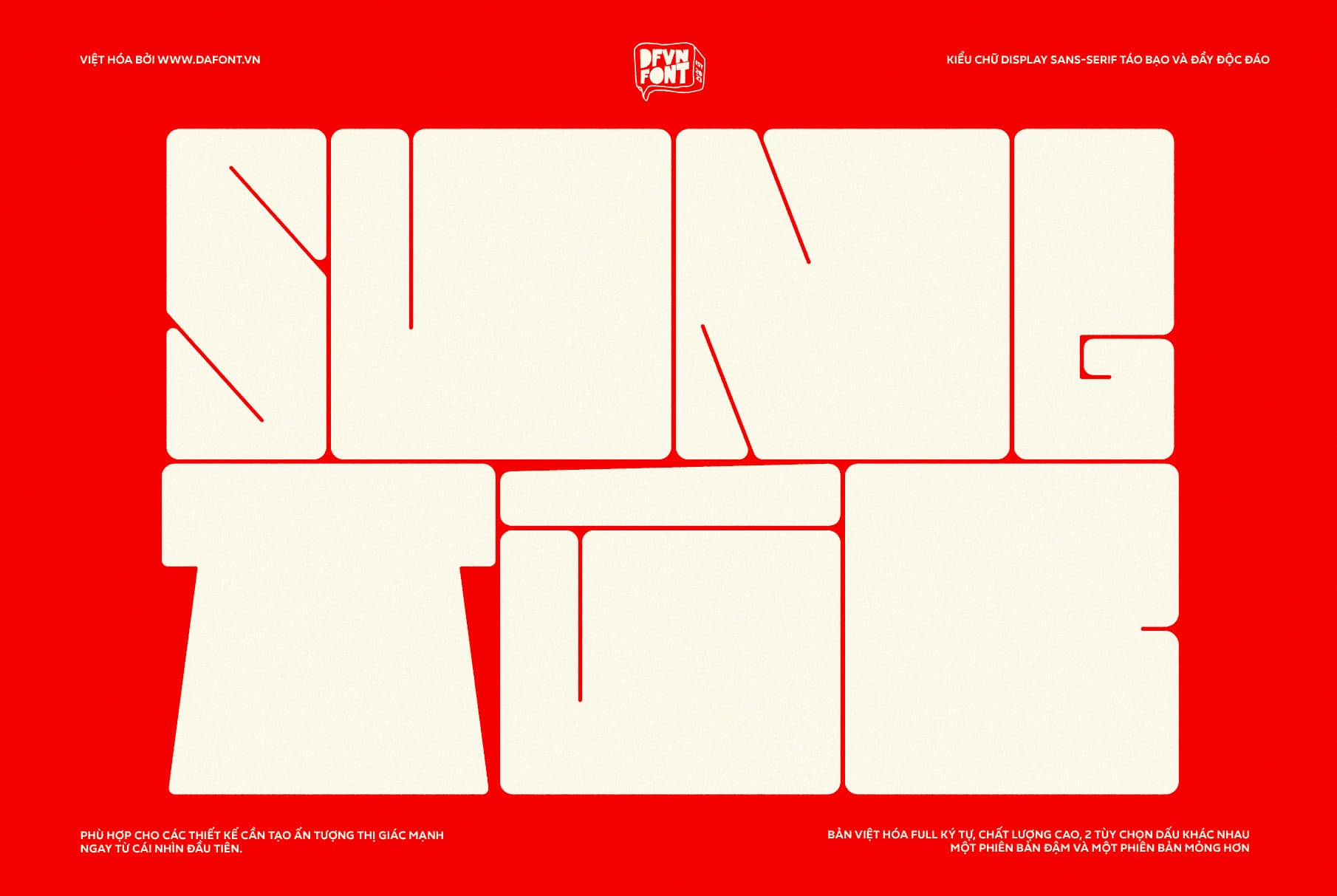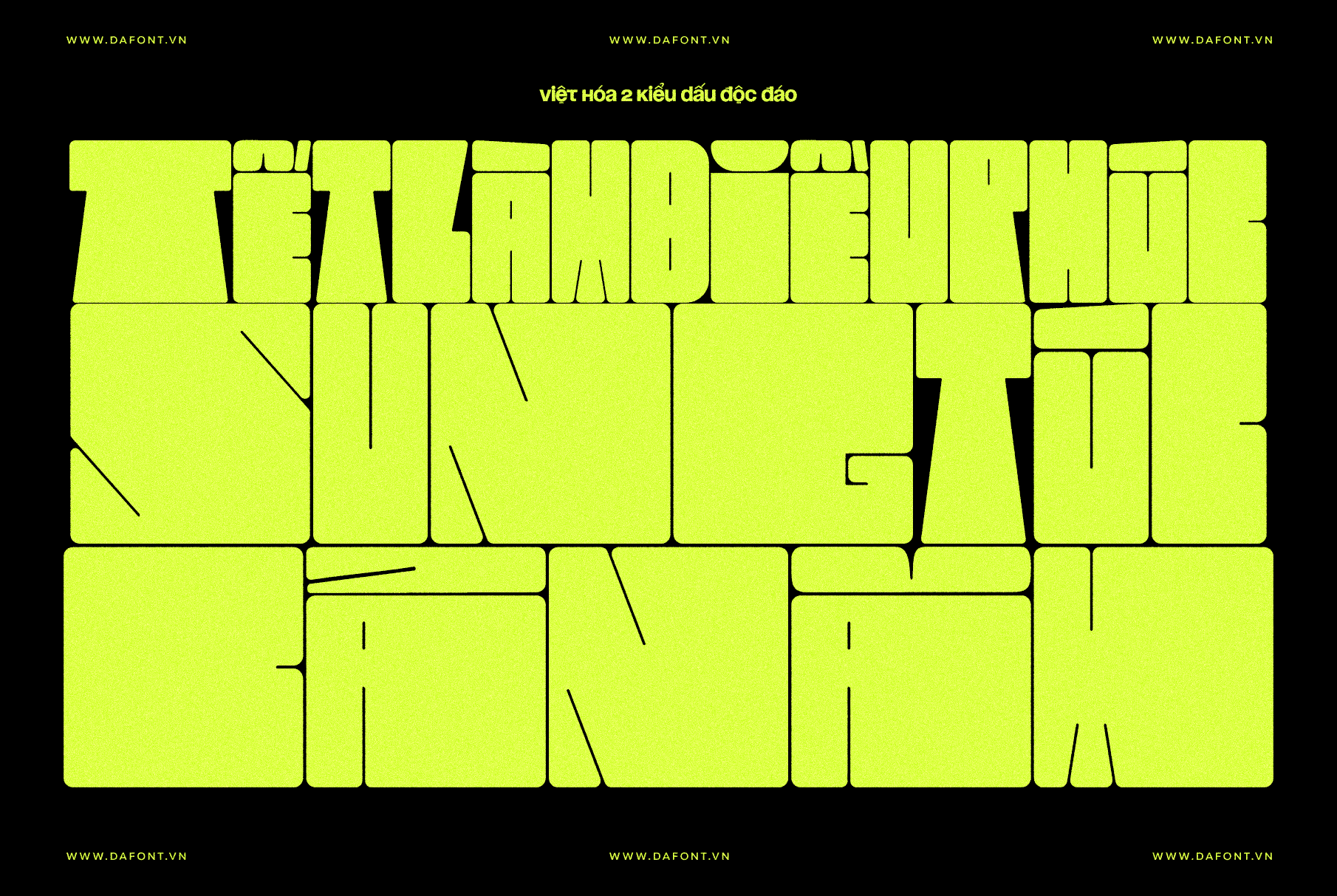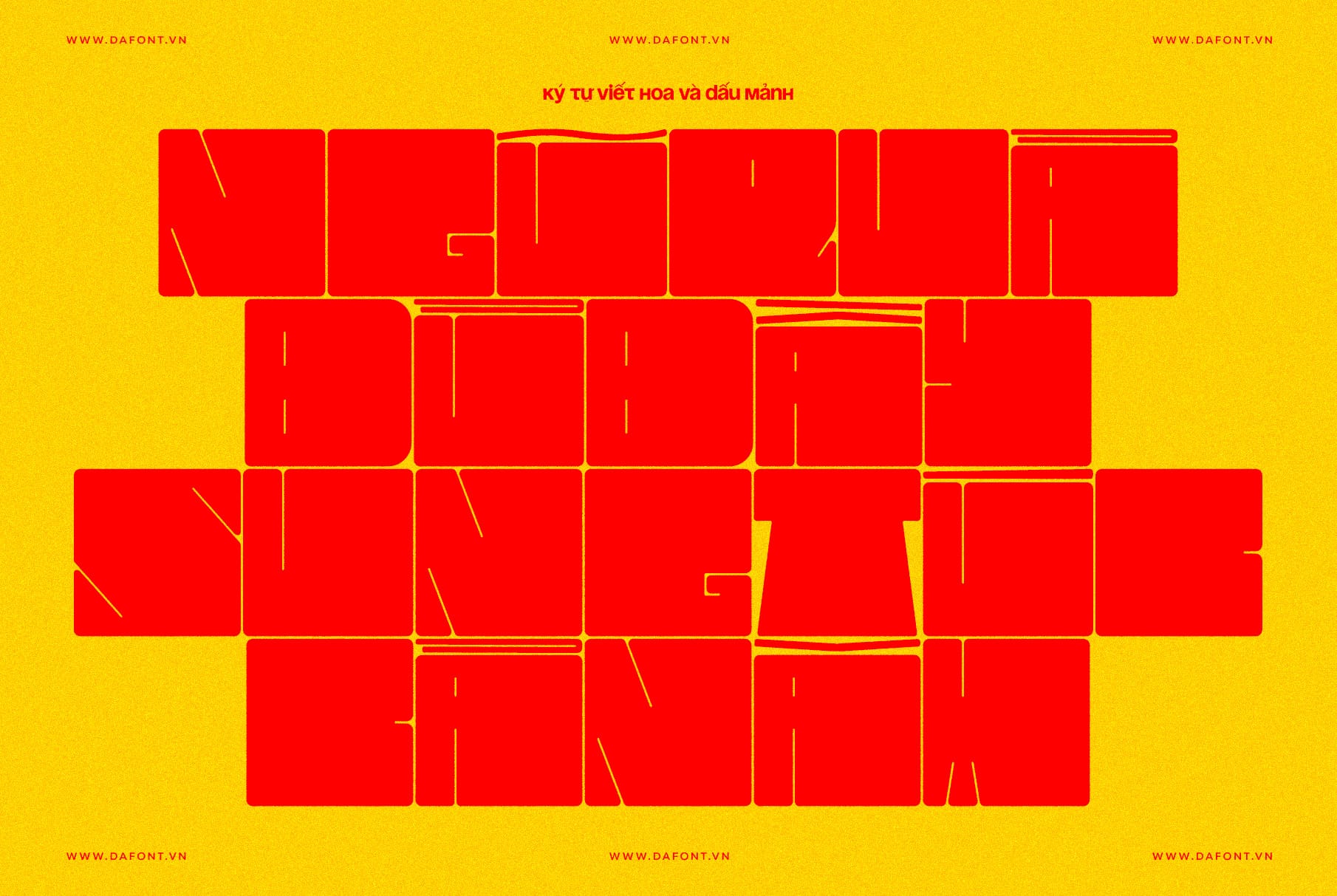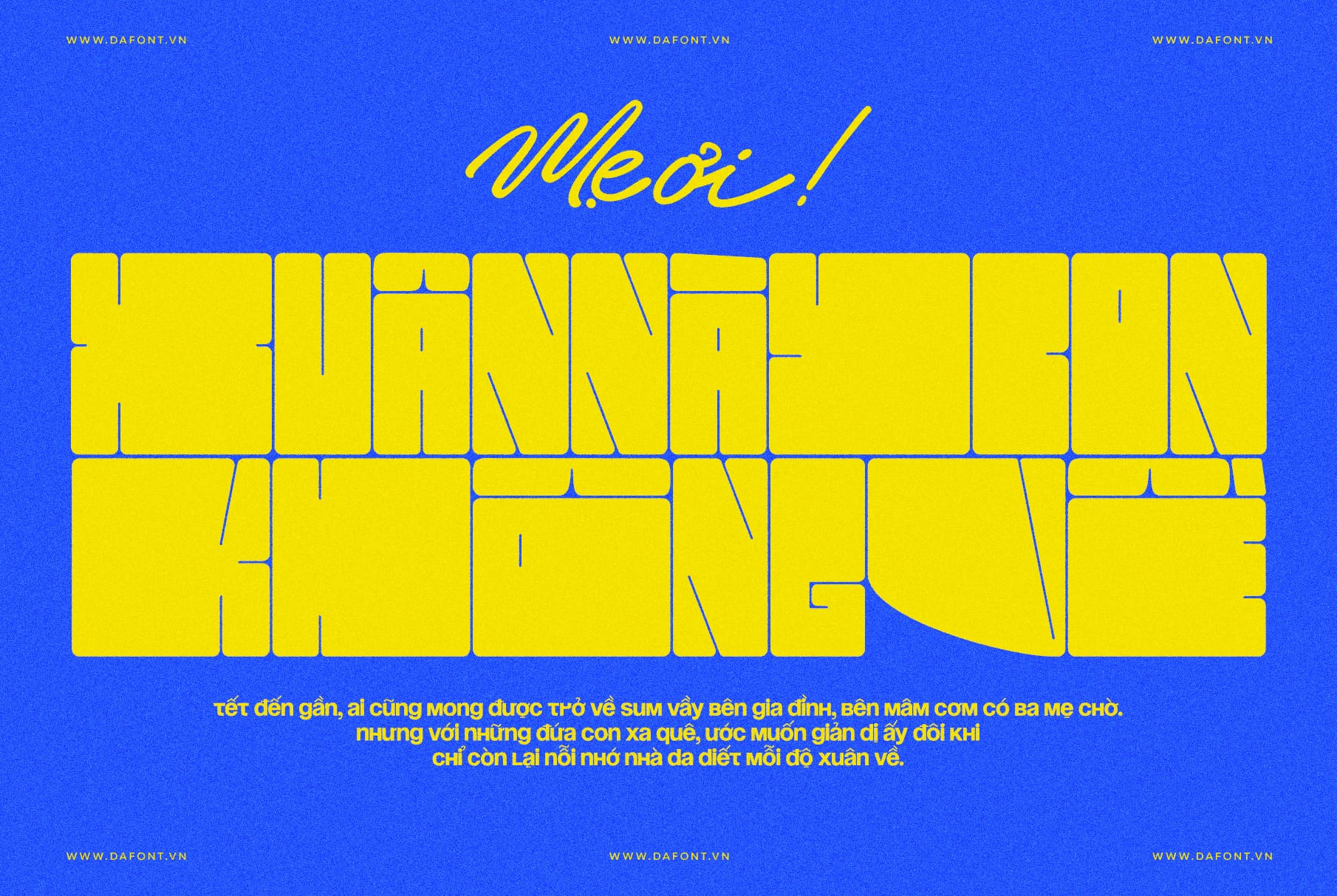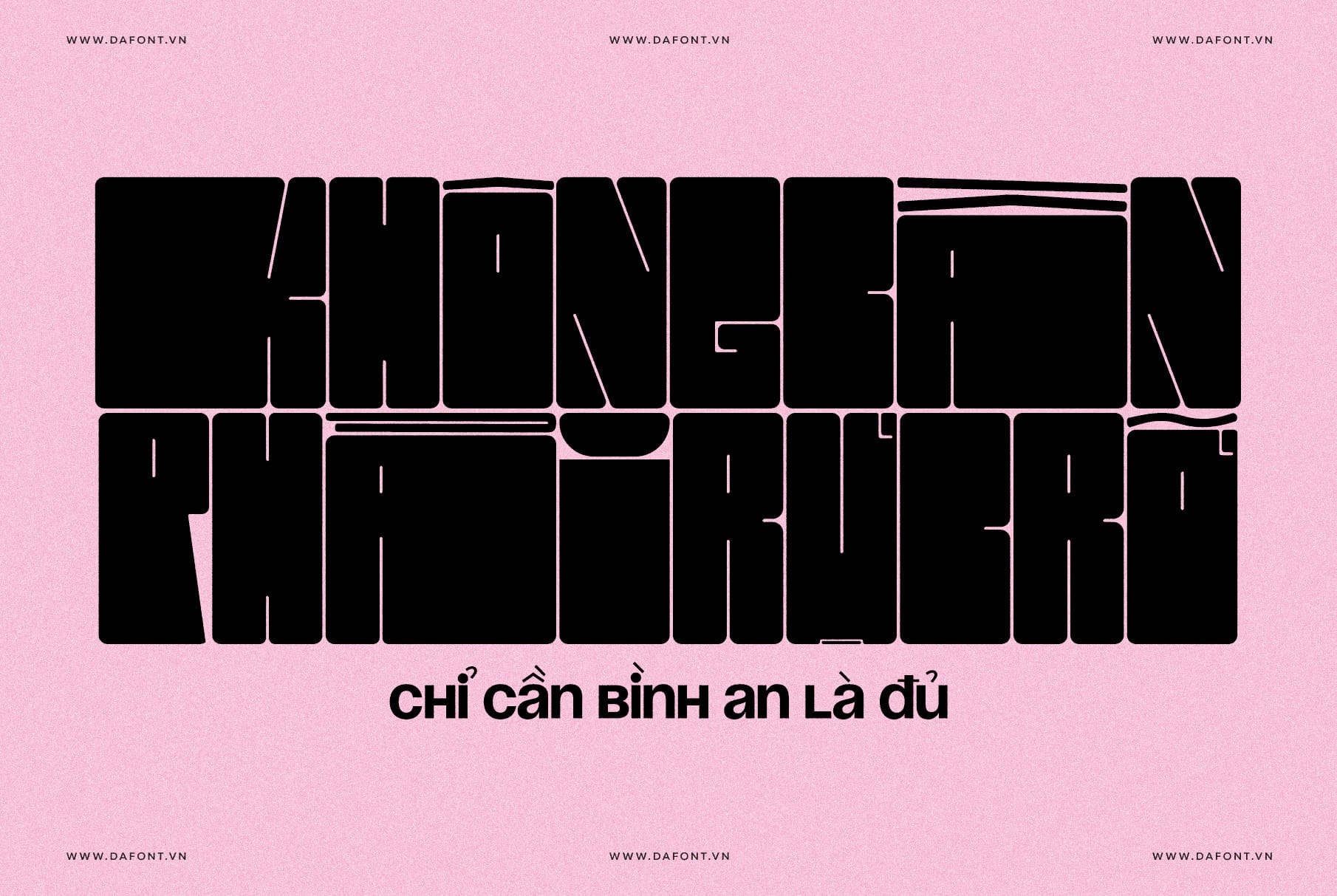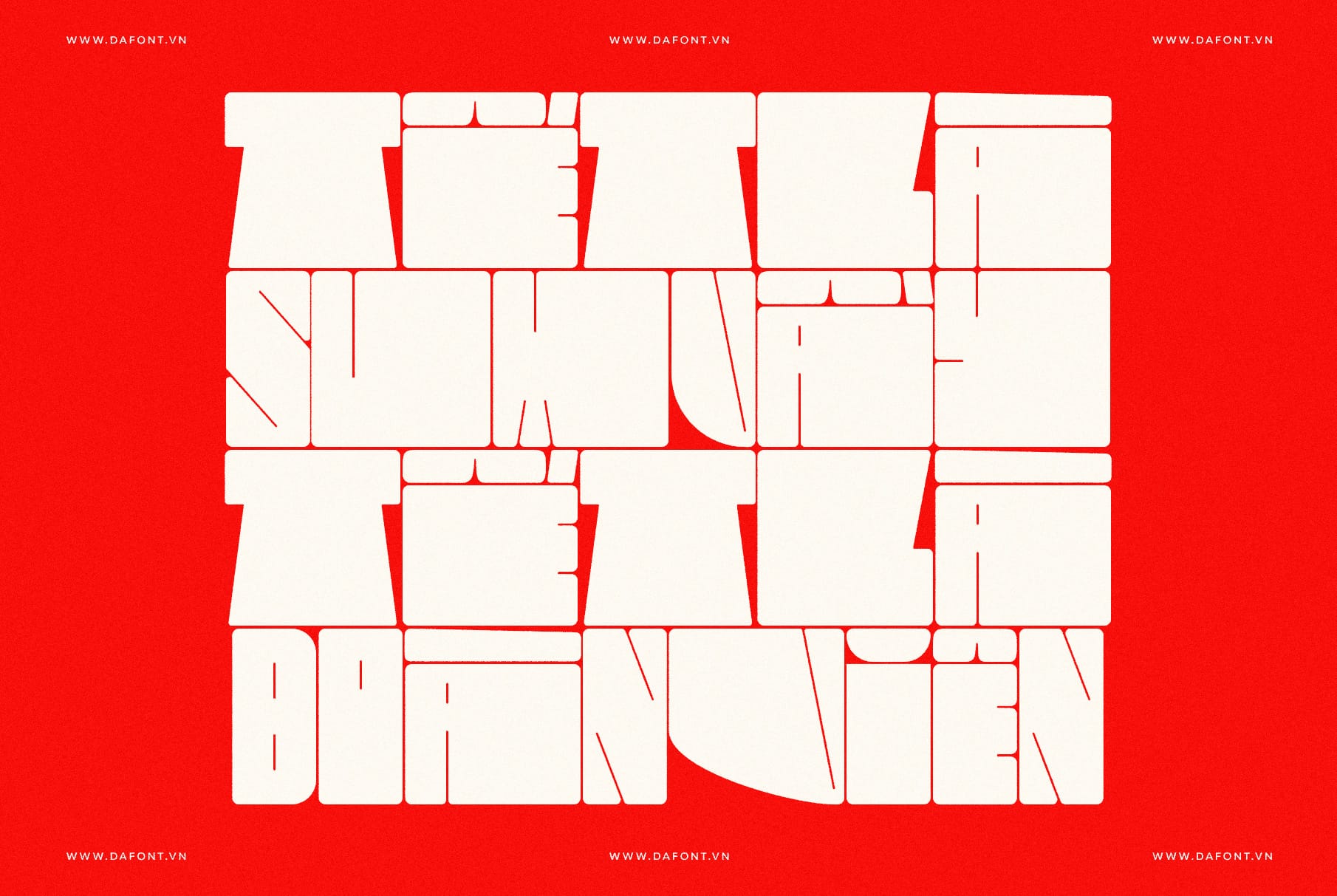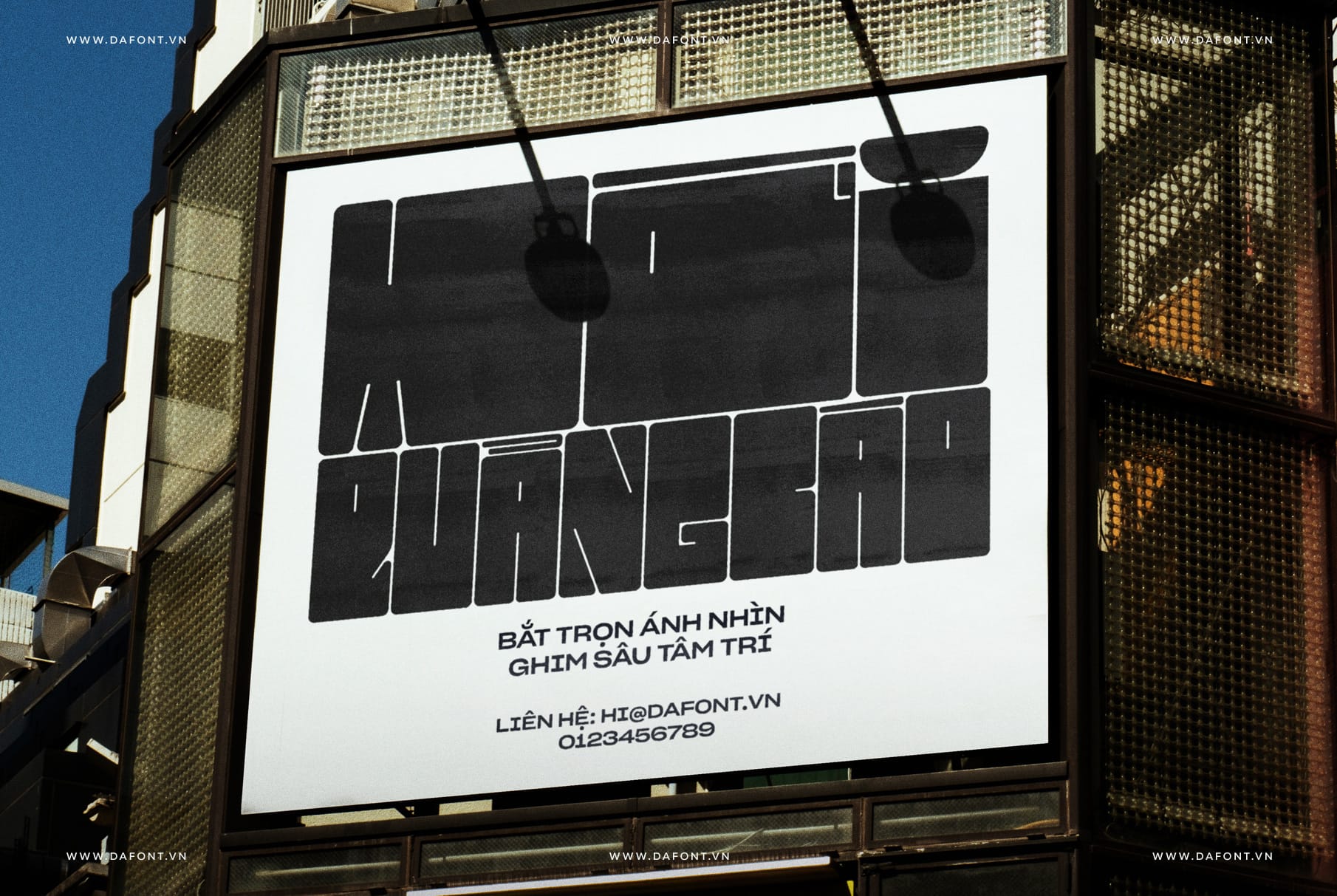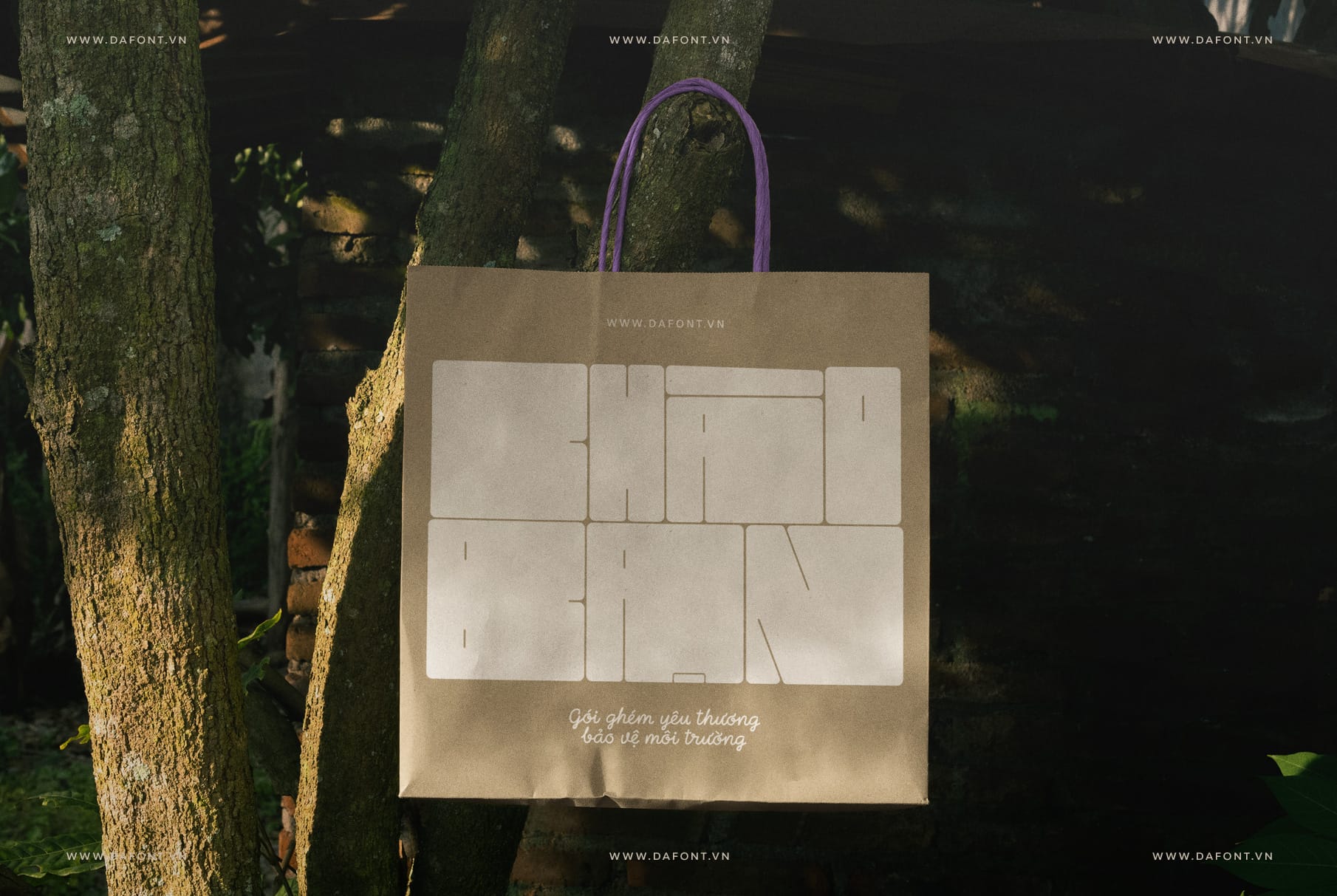
DFVN TF Browne (Teenage Browne) là một font chữ display sans-serif nổi bật mang tinh thần táo bạo, trẻ trung và hiện đại, sở hữu nét chữ dày, cấu trúc mạnh mẽ và cá tính rõ rệt, rất phù hợp cho các thiết kế cần tạo ấn tượng thị giác mạnh ngay từ cái nhìn đầu tiên
Đặc điểm nổi bật của DFVN TF Browne
1. Nét chữ dày, hình khối rõ ràng
TF Browne sở hữu stroke cực dày, cấu trúc chữ mạnh mẽ và độc lạ, giúp nội dung trở nên nổi bật ngay cả khi đặt trên nền đơn giản hoặc không gian lớn. Điều này khiến font rất hiệu quả khi dùng cho headline và logo.
2. Phong cách “edgy” và năng động
Font mang tinh thần trẻ, nổi loạn vừa đủ, không quá phá cách nhưng đủ khác biệt để tạo dấu ấn. Các chi tiết chữ được tối giản, thiên về hình học, giúp tổng thể gọn gàng mà vẫn mạnh mẽ.
3. Khả năng tạo điểm nhấn thị giác cao
DFVN TF Browne hoạt động tốt trong các layout cần độ tương phản cao, đặc biệt khi kết hợp với:
- Bố cục nhiều khoảng trắng
- Bảng màu tương phản hoặc đơn sắc
- Hình ảnh lifestyle, thời trang, urban
4. Linh hoạt trong nhiều ngữ cảnh thiết kế
Dù là display font, DFVN TF Browne vẫn dễ ứng dụng trong nhiều loại ấn phẩm khác nhau, từ in ấn đến digital, từ thương hiệu cá nhân đến chiến dịch quảng cáo.
DFVN TF Browne phù hợp với thiết kế nào?
TF Browne phát huy tối đa hiệu quả khi được sử dụng ở kích thước vừa đến lớn, đặc biệt trong các trường hợp:
- Logo & nhận diện thương hiệu: Thương hiệu thời trang, streetwear, sáng tạo, công nghệ
- Poster & banner: Sự kiện, triển lãm, âm nhạc, quảng bá sản phẩm, banner quảng cáo ngoài trời
- Bao bì & nhãn mác: Sản phẩm cần cá tính mạnh, khác biệt
- Social media & digital design: Thumbnail, key visual, headline
Font rất phù hợp với các thiết kế muốn truyền tải thông điệp tự tin - hiện đại - khác biệt.
Phiên bản Việt hóa chất lượng cao
DFVN TF Browne đã được Việt hóa đầy đủ, bao gồm:
- Hệ thống ký tự và dấu tiếng Việt hoàn chỉnh
- Toàn bộ ký tự và dấu tiếng Việt được tinh chỉnh kỹ lưỡng, căn chỉnh chuẩn xác
- Hiển thị ổn định trên nhiều nền tảng thiết kế và in ấn
- Khoảng cách ký tự và cấu trúc chữ được tối ưu lại
Ngoài ra, font còn cung cấp hai tùy chọn kiểu dấu (phiên bản đậm và phiên bản mảnh hơn), giúp người dùng linh hoạt lựa chọn theo từng ngữ cảnh sử dụng và phong cách thiết kế.
Lý do nên chọn DFVN TF Browne cho dự án thiết kế?
- Tạo ấn tượng mạnh mẽ ngay từ tiêu đề
- Phù hợp với xu hướng thiết kế hiện đại, tối giản nhưng cá tính
- Dễ kết hợp với không gian thoáng và bố cục tương phản
- Thích hợp cho các thương hiệu muốn thể hiện tinh thần trẻ và khác biệt
Kết luận
DFVN TF Browne font Việt hóa là một lựa chọn kiểu font hiển thị đáng giá cho những nhà thiết kế đang tìm kiếm một kiểu chữ mạnh mẽ, hiện đại và đầy cá tính. Với cấu trúc chắc chắn, nét chữ dày và độc đáo, font giúp thương hiệu và ấn phẩm thiết kế trở nên nổi bật, tự tin và khác biệt trong mọi ngữ cảnh sử dụng.
Nếu bạn đang cần một font chữ để “bật mood” cho logo, poster hay nhận diện thương hiệu, Teenage Browne chắc chắn là cái tên không nên bỏ qua.